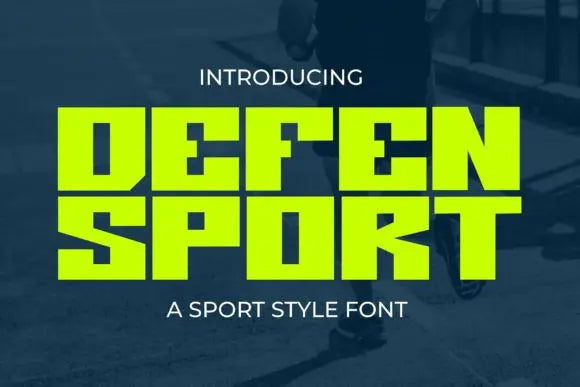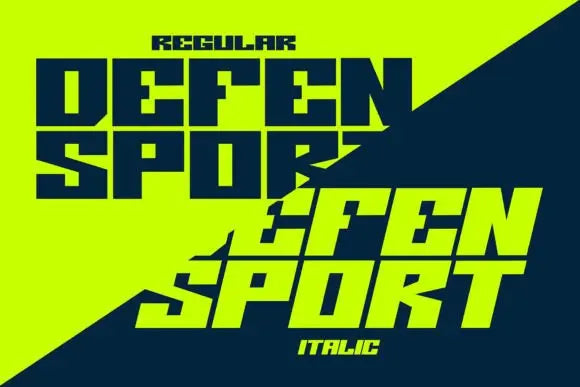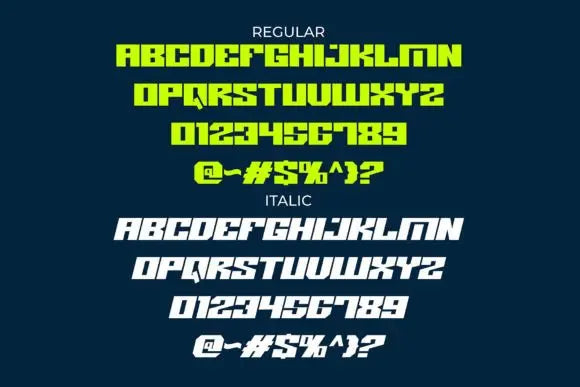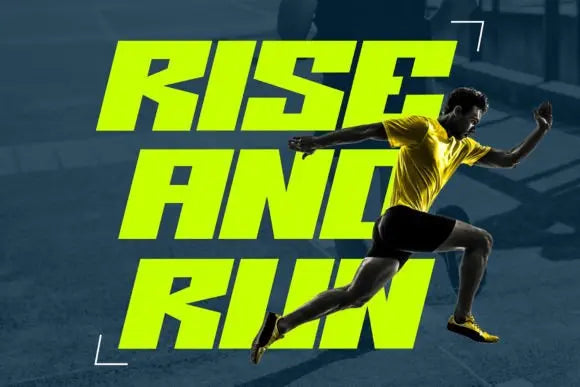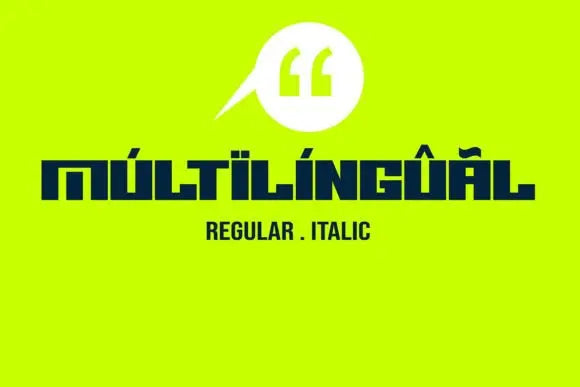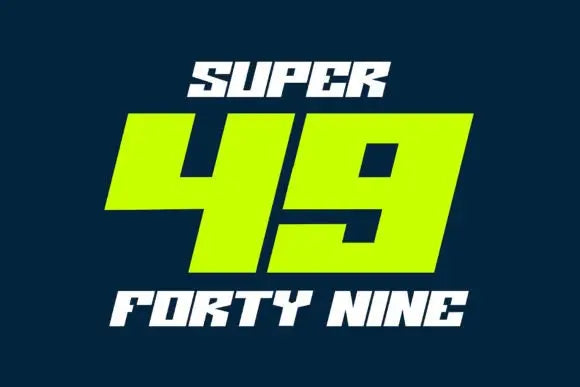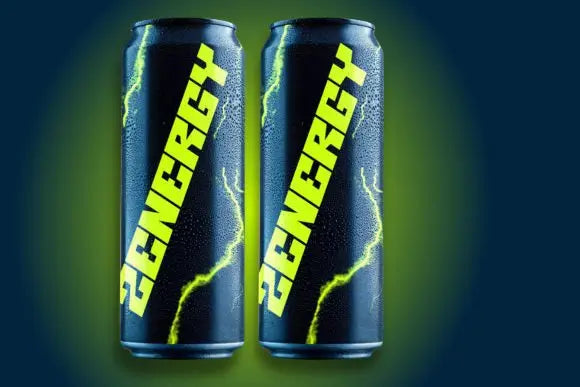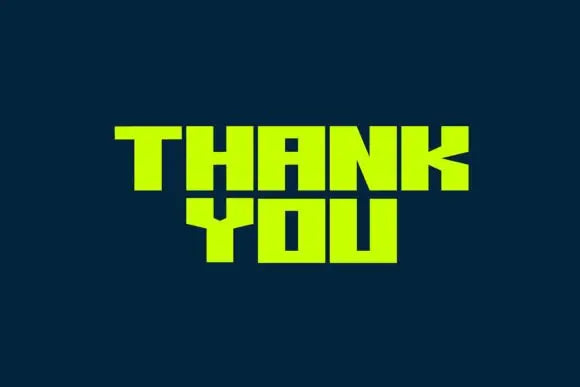
Fuente Defen Sport
Presentamos Defen Sport, una fuente vivaz y dinámica, meticulosamente seleccionada para reflejar un motivo deportivo enérgico. Caracterizado por expertos por sus estilos en negrita y cursiva, emana un aura de vigor, poder y atletismo. Tiene una inmensa presencia, cortesía de sus personajes robustos, al mismo tiempo que evoca una sensación de movimiento veloz y velocidad a través de su distintivo estilo en cursiva, capturando efectivamente la esencia central de los deportes competitivos.
Defen Sport es una estrella versátil en tipografía, ideal para infundir energía renovada y mayor emoción en una variedad de proyectos de diseño como pancartas deportivas, emblemas de equipos, carteles dinámicos o equipo deportivo de alto rendimiento.
Experimente el poder transformador de Defen Sport, una fuente que realmente encapsula el espíritu del juego con su brillo sorprendentemente audaz y dinámico.